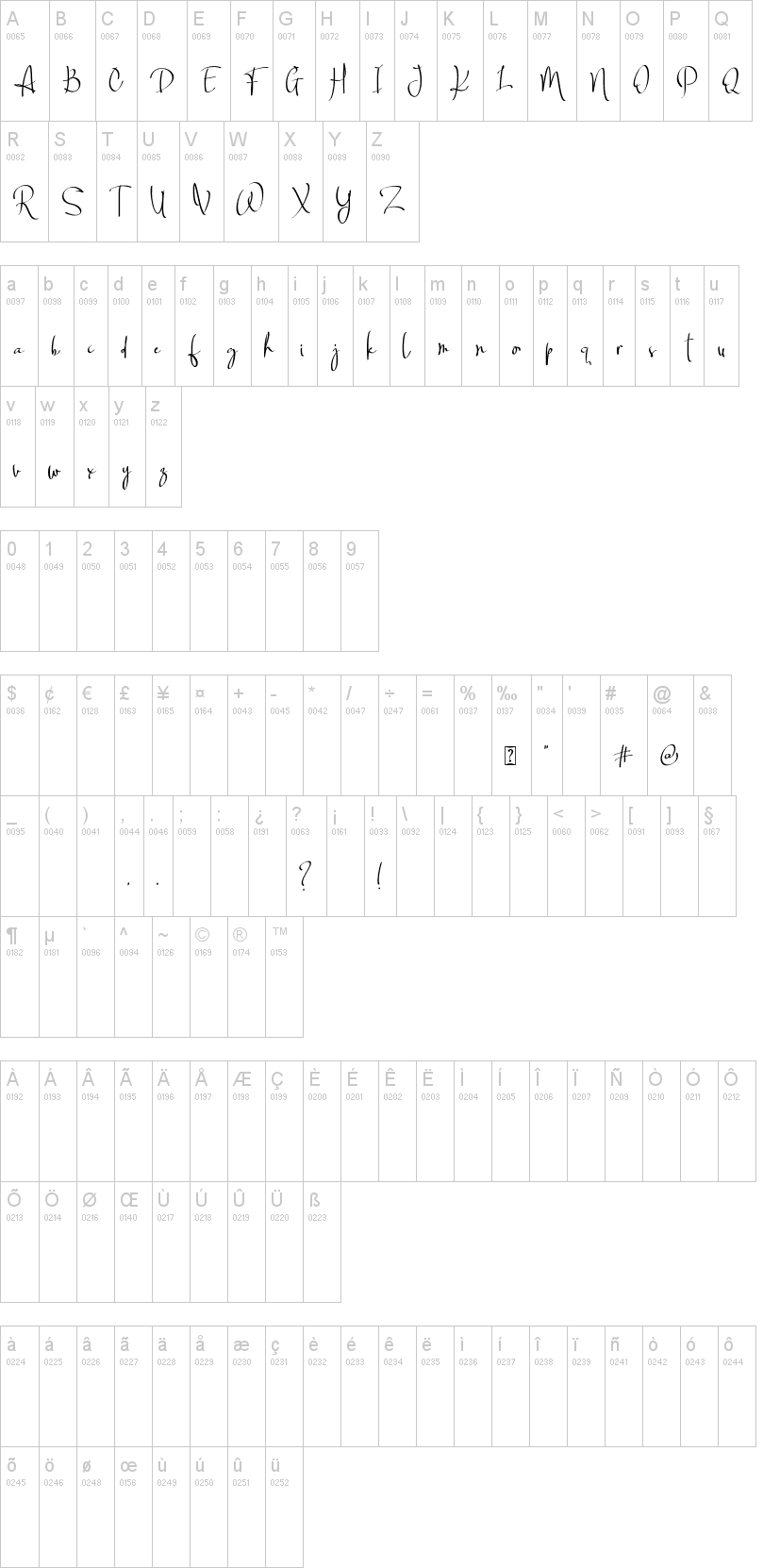
Billortte One
Billortte One 是一种可爱、有趣的手写风格字体,适用于各种设计项目。它具有自然的笔画和流畅的线条,对于需要突出文本的设计项目非常有用。Billortte One 字体在字母之间留有适当的间距,使得文字更易于阅读和辨识。除此之外,它还有一些额外的特性,例如一些可爱的装饰符号和一些字母的替代形式,这使得它更加多用途和有趣。它适用于卡片、海报、插图和品牌标识等多种设计场景,是一款非常优秀的字体选择。
Billortte One是一款非常不错的手写艺术字体,具有很好的视觉感,适合于文化类的宣传设计、商业类品牌的广告和产品包装设计以及个性化文字排版等较多场景。
Billortte One字符映射图